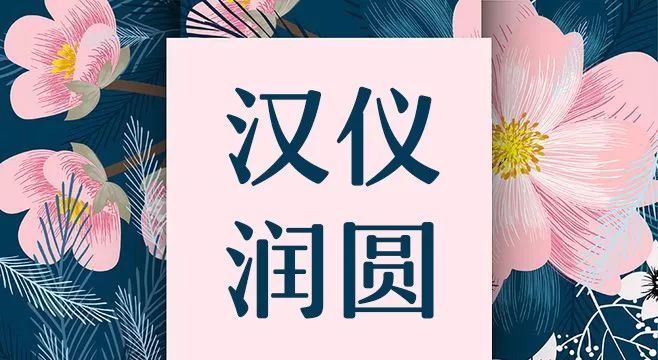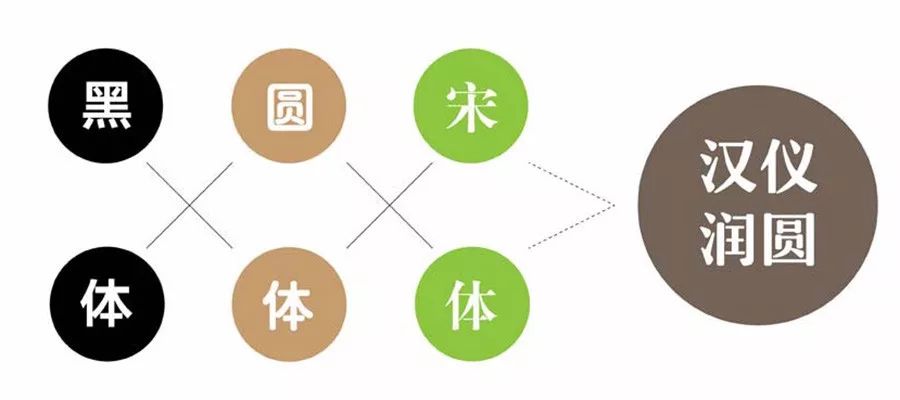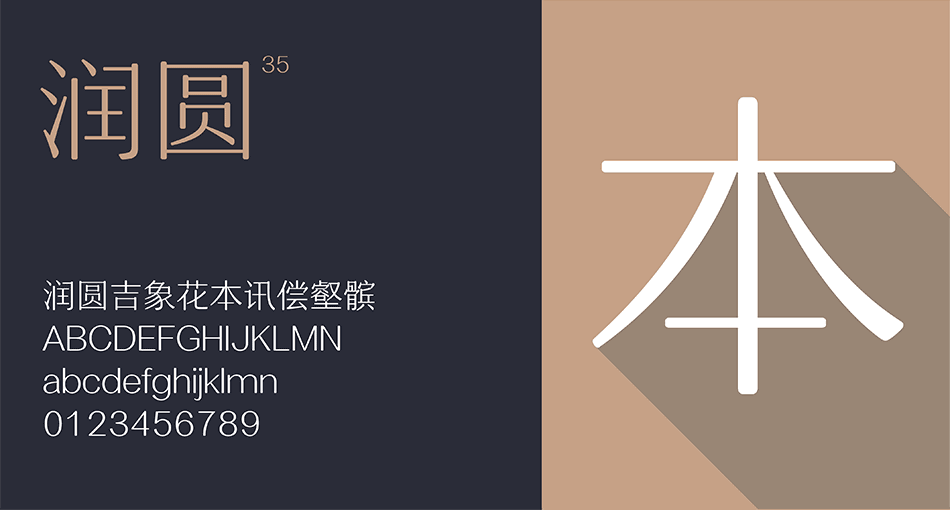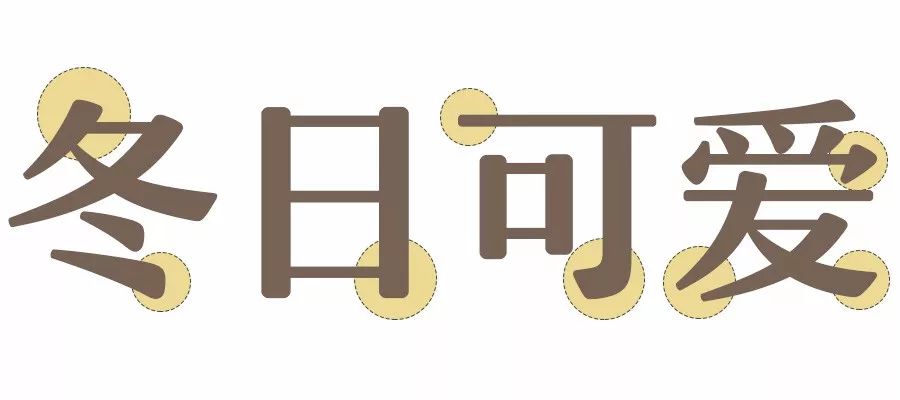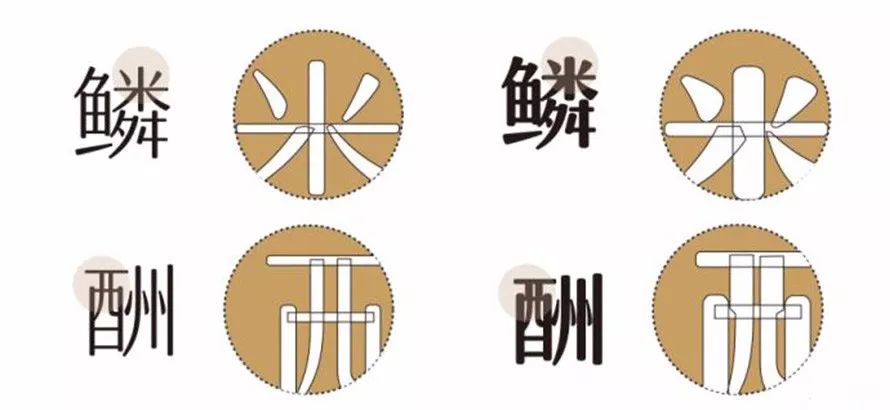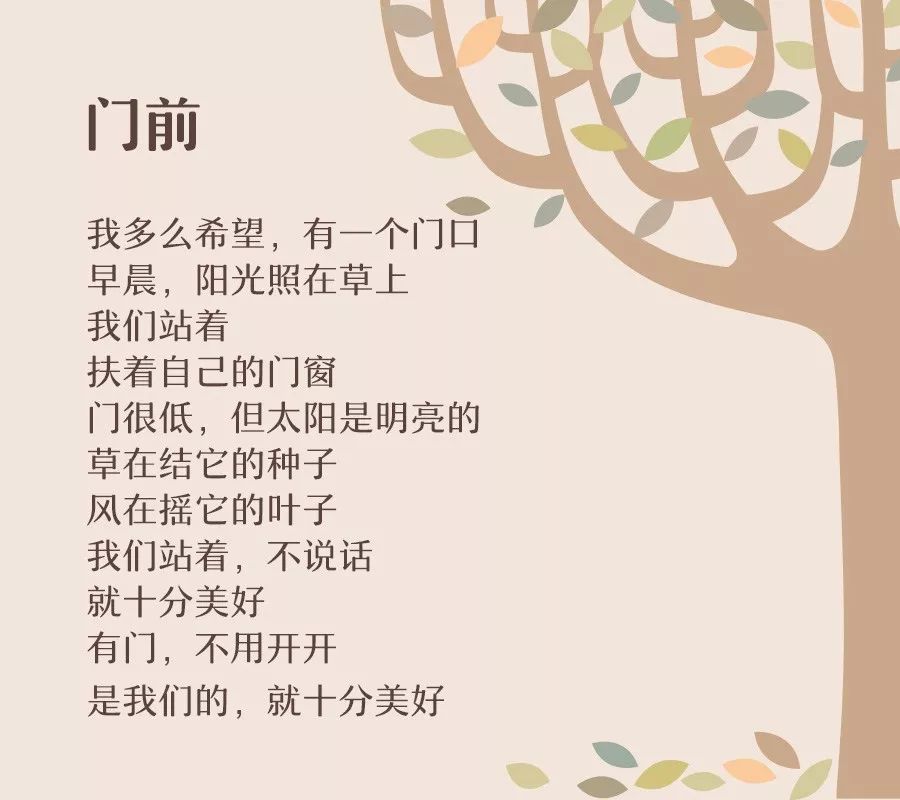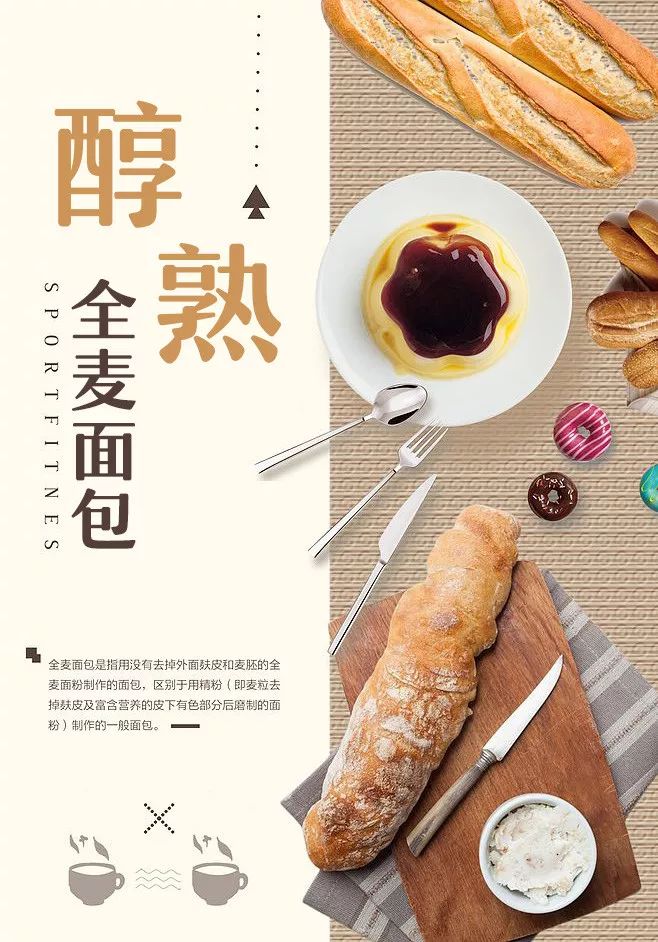
汉仪润圆使用案例,适合冬日的最佳字体
手里呀捧着窝窝头
菜里没有一点油
剁手后的日子是多么的苦呀
一想我就窝心头
~~~~~
😩
在这时
我遇见了生命中的那个她
她似一股春风拨动我的心弦
她的一举一动是如此优雅
醒醒嘞诶
你抱着我家展板乐半天了冻傻了吧!
你家展板的字用的汉仪润圆
太美了一时没忍住
👇
汉仪润圆在圆体基础之上加入
黑体与宋体的元素稳重而不失优雅
多款字重更好的适应不同环境的排版需要
字体笔画圆润舒展
略扁的字形让字体更加端庄稳重
不同字重细节处理区别35 VS 75
流畅的视觉重心
为阅读带来舒适的阅读体验
还没看够?
那再看看润圆更迷人的一面